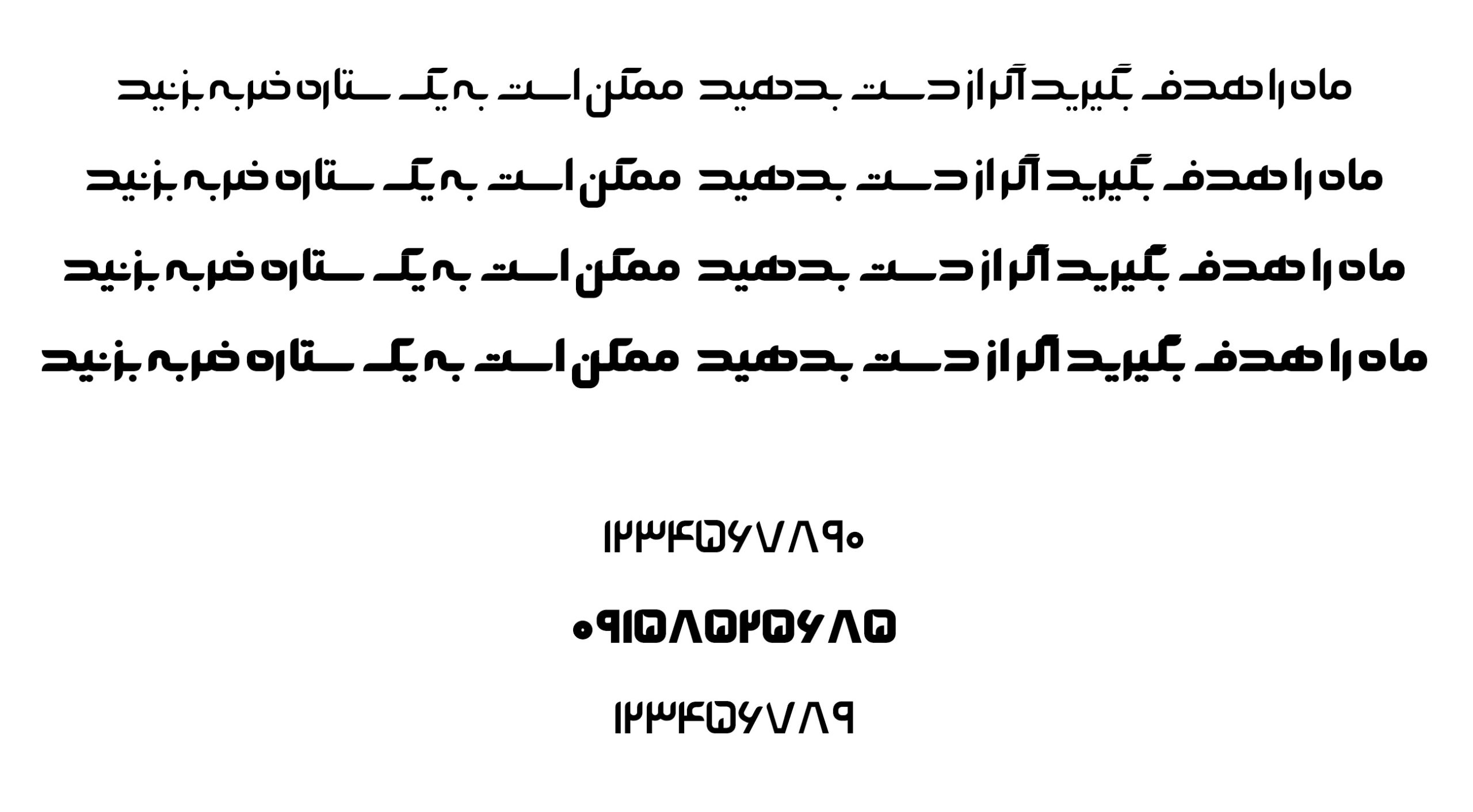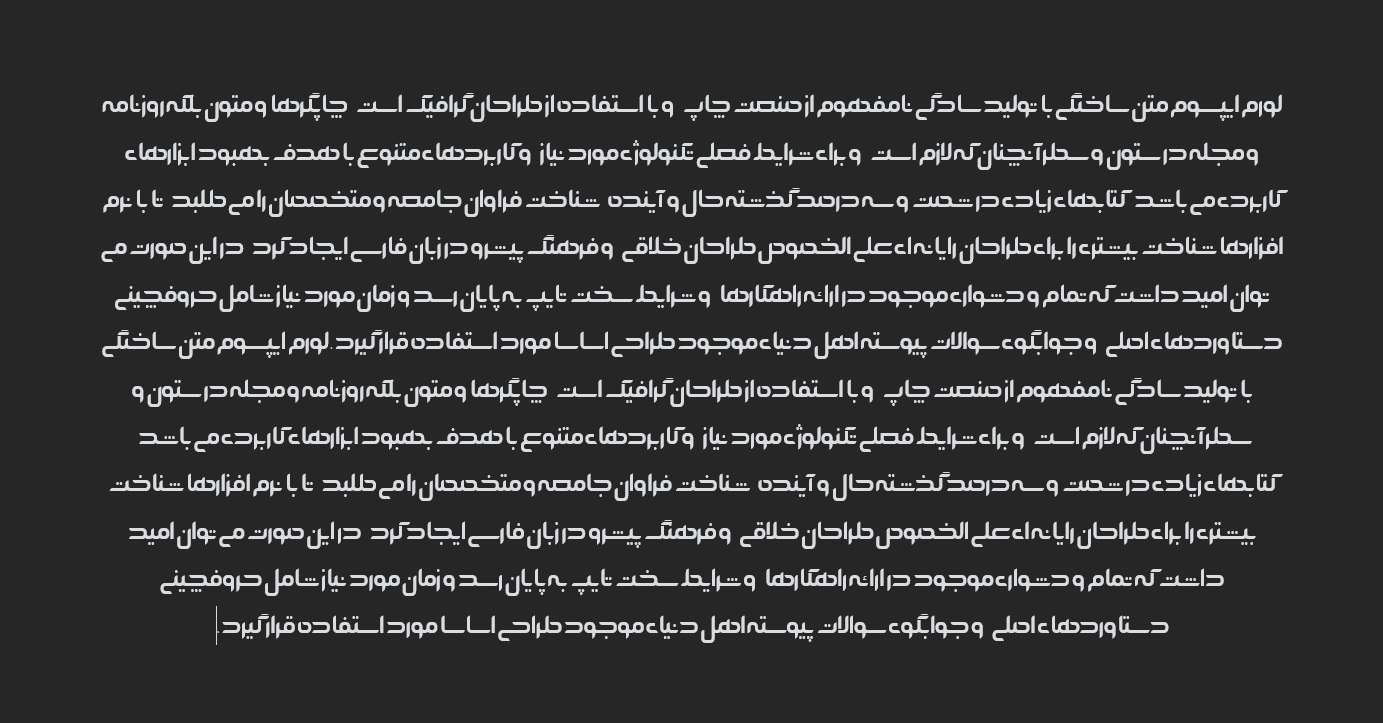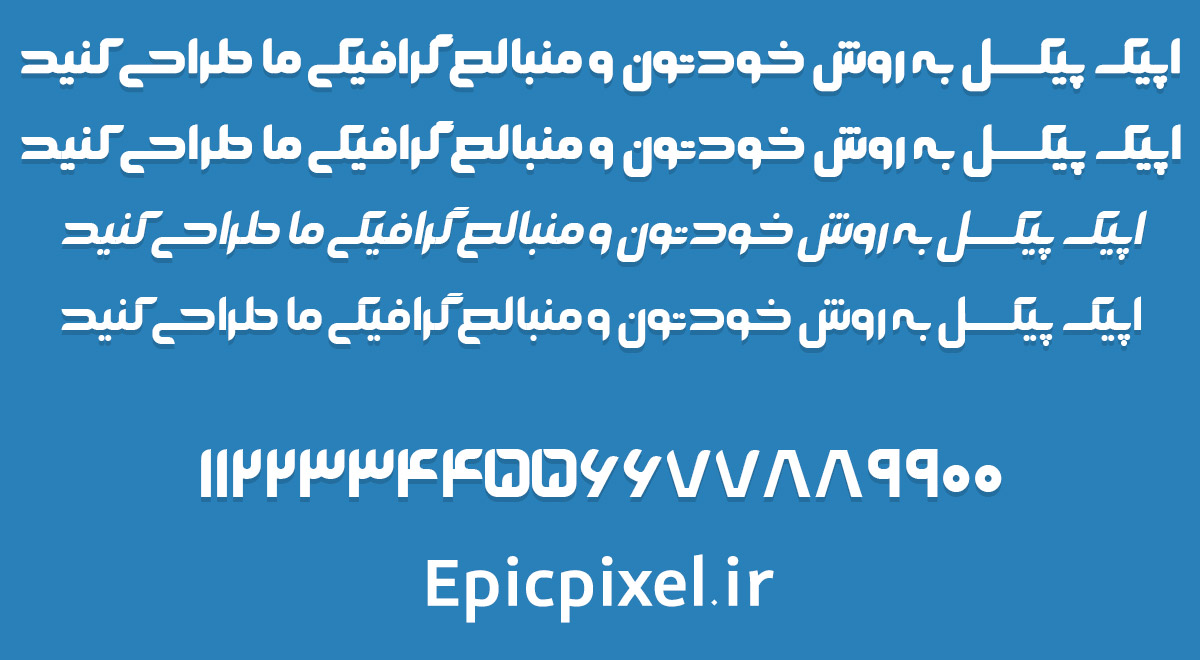
4 فونت نماوا فارسی
| ⭐ توضیحات | مجموعه ای کامل از فونت های نماوا و نسخه شبیه سازی شده بنام اپیک نماوا فونت اپیک نماوا با پشتیبانی از حروف فارسی ، اعداد فارسی Fu Num بهمراه نسخه وب بدون نسخه انگلیسی |
فونت نماوا یک فونت جدید و خلاقانه برای زبان فارسی
می خواهم با شما درباره یک فونت جدید و خلاقانه برای زبان فارسی صحبت کنم. این فونت به نام “فونت نماوا” شناخته می شود. این فونت با هدف ارائه یک رابط کاربری جذاب، مدرن و کارآمد برای وب سایت ها، اپلیکیشن ها، پروژه های گرافیکی و محصولات چاپی ساخته شده است. در این مقاله، من قصد دارم به شما معرفی، ویژگی ها، مزایا و راه های استفاده از این فونت را بگویم. اگر شما هم علاقه مند به آشنایی با این فونت هستید، با من همراه باشید.
معرفی فونت نماوا
فونت نماوا یک فونت ساده، شکلی و مینیمالیستی است که برای زبان فارسی طراحی شده است. این فونت از الگوهای هندسی و خطوط روان برای ساخت حروف استفاده می کند. این فونت به گونه ای طراحی شده است که هم با زبان فارسی و قوانین تایپ آن سازگار باشد و هم با زبان های دیگر مانند انگلیسی، عربی، ترکی و … هماهنگ باشد. این فونت دارای چند وزن مختلف است.
ویژگی های فونت نماوا
فونت نماوا دارای ویژگی های منحصر به فرد و جالبی است که آن را از فونت های دیگر متمایز می کند. برخی از این ویژگی ها عبارتند از:
دانلودپشتیبانی از علائم نگارشی. فونت نماوا به طور کامل از علائم نگارشی مانند نقطه، ویرگول، خط تیره، پرانتز، کروشه، نقل قول، علامت سؤال، علامت تعجب، علامت درصد، علامت تجاری و … پشتیبانی می کند. علائم نگارشی فونت نماوا با حروف آن همسانگام شده اند و در جای مناسب قرار گرفته اند.
پشتیبانی از عددها. فونت نماوا به طور کامل از عددهای فارسی پشتیبانی می کند. عددهای فونت نماوا با حروف آن همخط شده اند و در جای مناسب قرار گرفته اند. همچنین شما می توانید بین عددهای فارسی راحت جابجا شوید.
پشتیبانی از سمبل ها. فونت نماوا به طور کامل از سمبل های رایج مانند دلار، یورو، پوند، چینی، استرلینگ، ریال، روپیه، یوان، یکه و … پشتیبانی می کند. سمبل های فونت نماوا با حروف آن همخط شده اند و در جای مناسب قرار گرفته اند. همچنین شما می توانید بین سمبل های مختلف راحت جابجا شوید.
پشتیبانی از اشکال هندسی. فونت نماوا به طور کامل از اشکال هندسی مانند دایره، مربع، مثلث، بیضی، خط، نقطه و … پشتیبانی می کند. اشکال هندسی فونت نماوا با حروف آن همسانگام شده اند و در جای مناسب قرار گرفته اند. همچنین شما می توانید بین اشکال هندسی مختلف راحت جابجا شوید.
پشتیبانی از آیکون ها. فونت نماوا به طور کامل از آیکون های معروف و پرکاربرد مانند دل، ستاره، گلوله، تیک، باترفلای، فلش، پلاس، منها و … پشتیبانی می کند. آیکون های فونت نماوا با حروف آن همخط شده اند و در جای مناسب قرار گرفته اند. همچنین شما می توانید بین آیکون های مختلف راحت جابجا شوید.
تاریخچه و اهداف فونت نماوا
فونت نماوا در سال 2023 طراحی شده است.با تحقیقات و بررسی های گسترده در زمینه زبان فارسی و فونت های موجود، به این نتیجه رسیدیم که بسیاری از فونت های فارسی که در حال حاضر استفاده می شوند دارای مشکلات و نقص های زیر هستند:
دانلودعدم خلاقیت و تکرار. بسیاری از فونت های فارسی کپی یا الهام گرفته از فونت های قدیمی و سنتی مانند نستعلیق، نسخ، ثلث و … هستند و دارای تغییرات جزئی و بی روح هستند. این باعث شده است که فضای تایپ فارسی خسته کننده و monotone باشد.
عدم سازگاری با زبان های دیگر. بسیاری از فونت های فارسی با زبان های دیگر مانند انگلیسی، عربی، ترکی و … هماهنگ نیستند و در نوشتن متون چند زبانه باعث اختلال و ناهماهنگی می شوند. این مشکل به خصوص در زمینه طراحی وب و اپلیکیشن ها که نیاز به رابط کاربری چند زبانه دارند، حساس است.
عدم رعایت قوانین تایپ و زبان فارسی. بسیاری از فونت های فارسی با قوانین تایپ و زبان فارسی سازگار نیستند و باعث اشتباهات و خطاهای نگارشی می شوند. برخی از این خطاها عبارتند از: عدم رعایت فاصله بین حروف، عدم رعایت ارتفاع و عرض حروف، عدم رعایت تراز حروف، عدم رعایت جهت حروف، عدم رعایت شکل حروف در موقعیت های مختلف و …
افزایش خلاقیت و تنوع در فضای تایپ فارسی. فونت نماوا با استفاده از الگوهای هندسی و خطوط روان، یک فونت ساده، شکلی و مینیمالیستی است که با فونت های سنتی و قدیمی فارسی تفاوت دارد. این فونت با ارائه یک شکل جدید و مدرن برای حروف فارسی، قصد دارد که خلاقیت و تنوع را در فضای تایپ فارسی افزایش دهد.
افزایش سازگاری با زبان های دیگر. فونت نماوا با پشتیبانی کامل از حروف لاتین، علائم نگارشی، عددها، سمبل ها، اشکال هندسی و آیکون ها، چه در زبان فارسی و چه در زبان های دیگر، یک فونت یکنواخت و هماهنگ است. این فونت با حفظ تناسب و همسانگامی بین حروف فارسی و لاتین، امکان نوشتن متون چند زبانه را به راحتی فراهم می کند. این فونت به خصوص برای طراحان وب و اپلیکیشن ها که نیاز به رابط کاربری چند زبانه دارند، مناسب است.
دانلودافزایش رعایت قوانین تایپ و زبان فارسی. فونت نماوا با رعایت دقیق قوانین تایپ و زبان فارسی، یک فونت صحیح و بدون خطا است. این فونت با رعایت فاصله بین حروف، ارتفاع و عرض حروف، تراز حروف، جهت حروف و شکل حروف در موقعیت های مختلف، امکان نوشتن متون خوانا و قابل فهم را به شما می دهد.